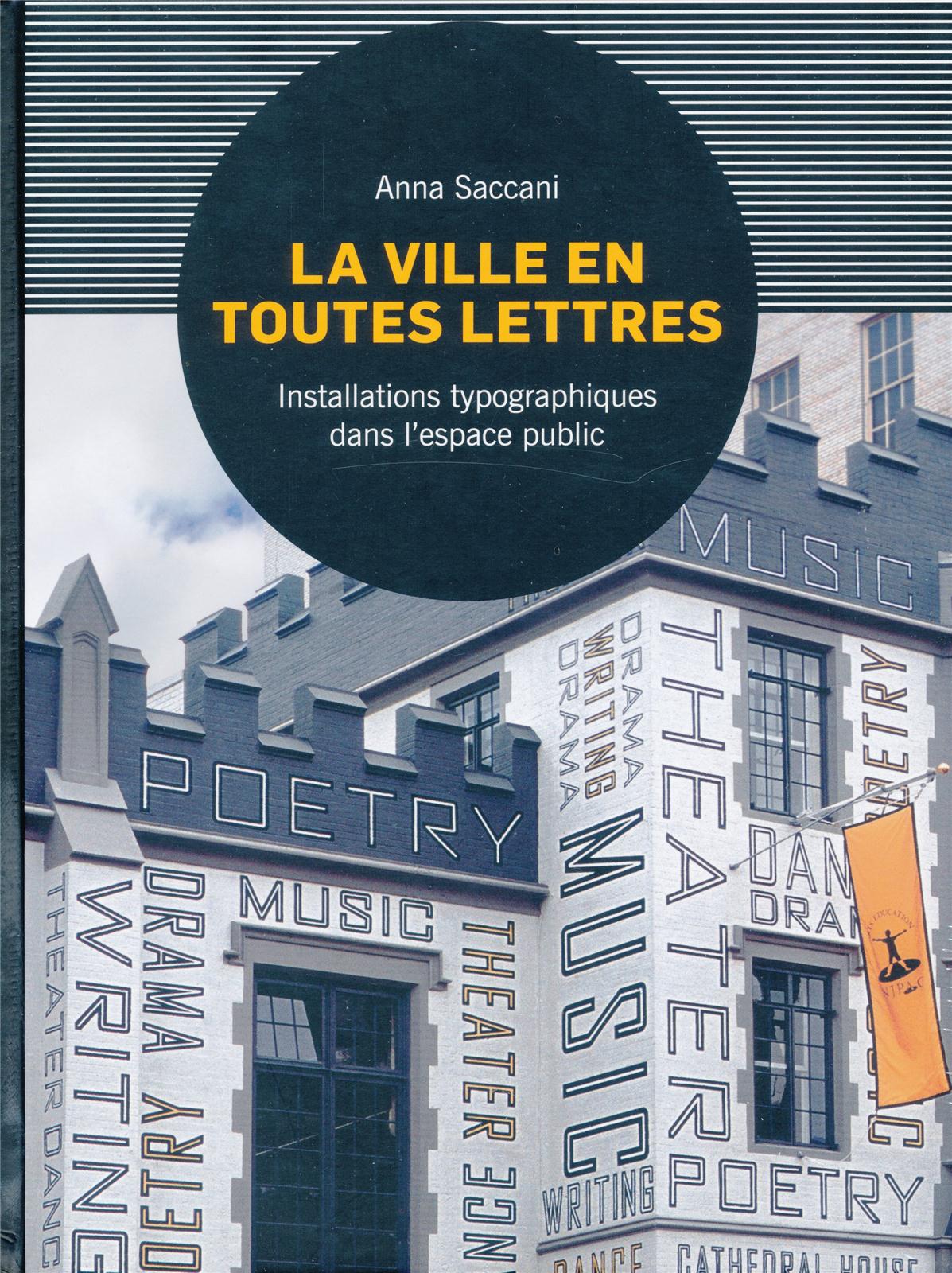
LA VILLE EN TOUTES LETTRES
La ville en toutes lettres présente 37 projets mêlant la typographie et le lettrage au paysage urbain. Au croisement de l'art, de la typographie et de l'architecture, les projets présentés dans cet ouvrage donnent une dimension nouvelle au mot écrit et aux caractères. Chiffre géant, sculpture en braille, citations placées au sol et installations poétiques forment autant de points de repère, de réflexion ou de rêverie au sein des espaces urbains.
Dans ces villes ponctuées par le lettrage, les noms des victimes de drames s'affichent sur les murs, l'heure se lit sur la façade des immeubles et les plaques d'égout se font oeuvres d'art. L'auteure nous invite ainsi, de New York à Barcelone en passant par Séoul, à un voyage artistique, historique et empreint d'émotions. Quand les installations typographiques s'emparent de l'espace de nos villes, ce sont en effet la mémoire et la poésie qui y rythment nos pas.
La présentation des projets est complétée par des interviews des créateurs et par des données sur les artistes impliqués et les caractères utilisés.